数字
对于字体设计者来说数字经常是困难的–原因有几点。一个原因是数字有大量的曲线。另一个原因是数字经常在他们的形状中使用的约定与在字体设计的其他部分中可见的约定不同(甚至是违背)。此外,数字可能有非常大量的笔画(像 8 和 5 那样),或者他们有大片的空白空间(像 1,7,有时包括 2 和 4)。两种情况都可能难以处理。最后还有一个问题,如何让零看起来与大写字母 O 不同。
看各种各样字体中的数字从而对设计者们应对这些问题的的方式更加熟悉,这样做是有帮助的。
在笔画密集的数字(比如 8)中,你可能发现设计者们允许笔画宽度变得比字体中的典型字母更细。类似的方法也可以在双眼的 g 种看到。
相反,为了补偿空白空间比例大的数字,一些笔画很可能比典型的更重。
区分零和大写字母 O 有广泛的解决方案–比如将零做得比 O 窄,或者零做成完美的圆,或者可能有斜线穿过零(尤其是 monospace 字体)。
零比大写的 O 更窄但是高度相同是通用的方法。这是衬里数字的典型方法。衬里数字(Lining Numberal)是数字最通用的样式。使用这种方法的字体包括:许多 Garamonds、Futura 和 Google 的网页字体 Open Sans。下面是 Open Sans 字体展示的零、大写字母 O,然后是其他数字。
一个完美的圆或者接近完美的圆圈不常用,但是也存在。使用这种方法的字体的例子包括 Google 网页字体 Vollkorn 和其他商业字体比如 Mrs Eaves,Vendeta 和 Fleischman BT Pro。使用老式的按比例的数字的字体更多地使用了这种方法。有时也会看到一个达到 x 高度但是更窄的零。
当你包含了分数、上标和下标的时候,数字可能有多达 11 种可以分辨的样式。我们来看其中 5 种最常见的。
衬里样式数字
字体中见到的最常用的样式是扁平衬里(Tabular Lining)和比例衬里(Proportional Lining)。衬里指的是数字使用的高度。衬里样式指的是所有数字的高度视觉上一致。扁平衬里和比例衬里数字的区别是扁平衬里中所有的数字共享宽度。这个样式的用处在于电子扁平和其他数字堆叠在整齐的水平和竖直线上有好处的地方。
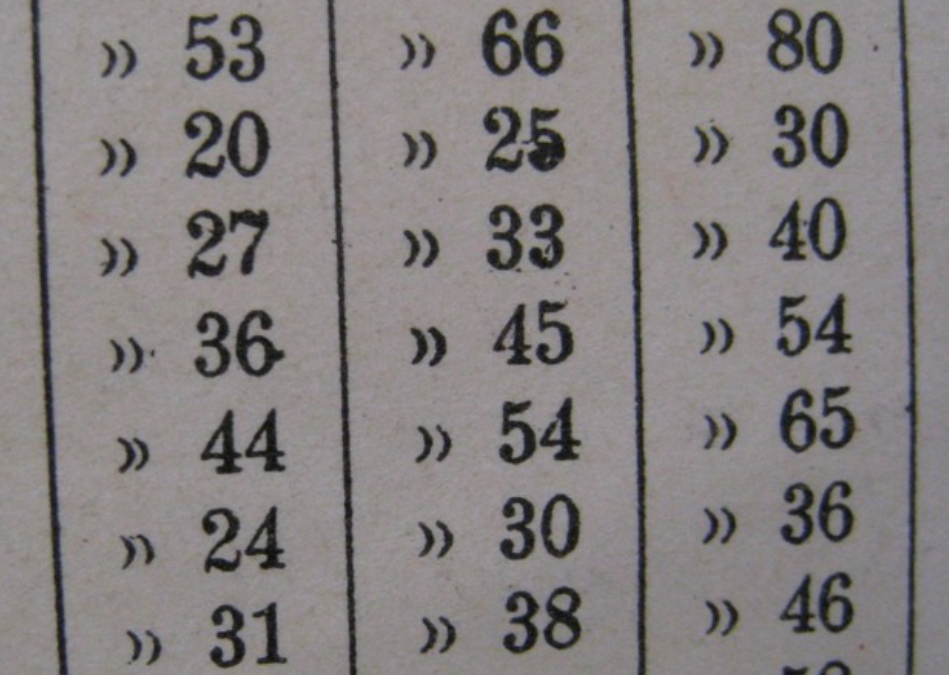
比例衬里数字的好处在于其看起来更相等,因为数字的形式和间距可以补偿不同的笔画密度。
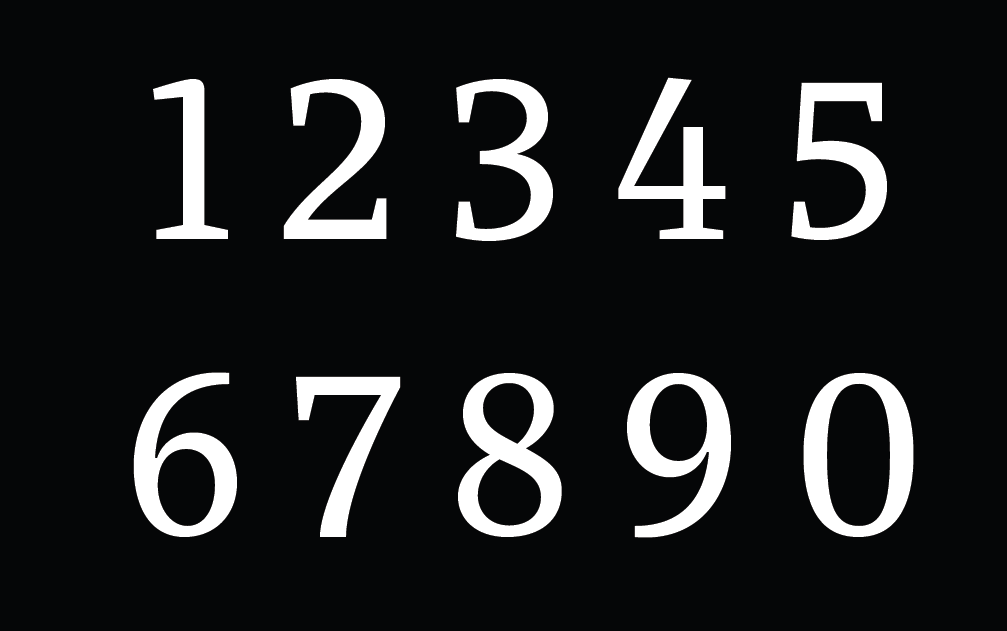
排列或者老式的数字
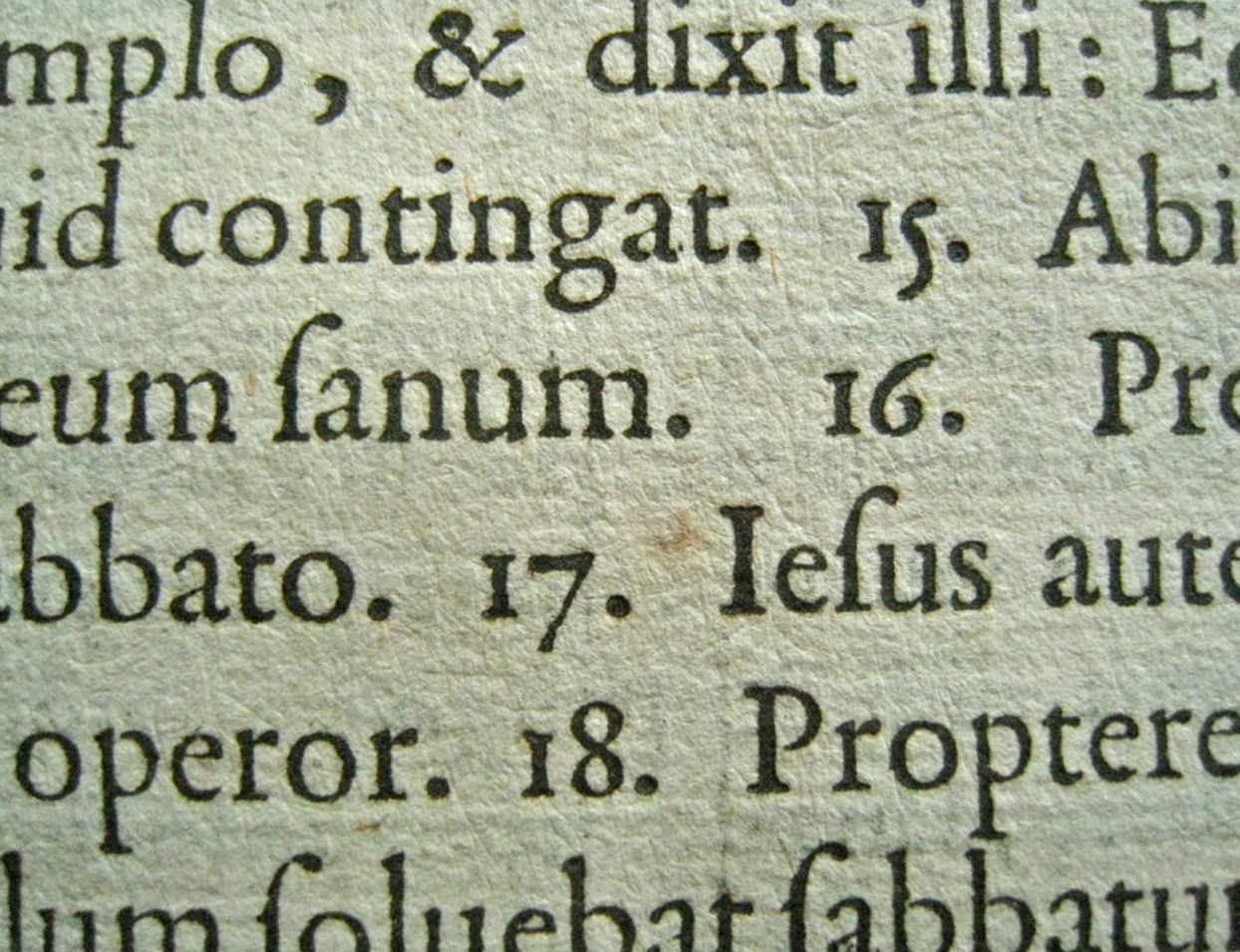
扁平数字是历史上的术语中相对较新的发明。在其存在前有许多老式的比例数字。如果你希望数字和文字混合并使用文字的样式,那么老式的数字是有帮助的。
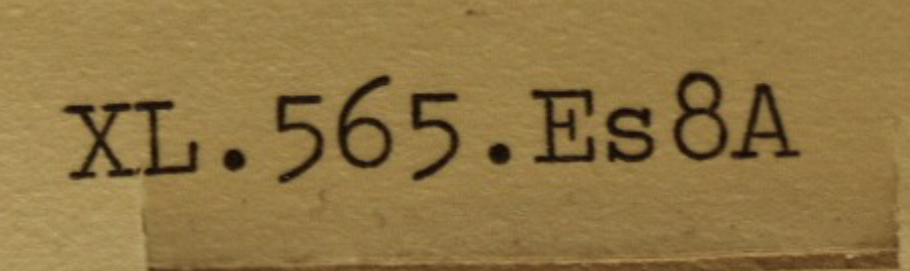
扁平老式数字是非常少见的。它在年报中有用,在年报中你想要老式数字的感觉,扁平间距是这种类型文件的典型。上面的图片来自打印机制作的图书馆分类卡。
混合类型数字
混合(hybrid)数字并不使用字体的大写高度和 x 高度,而是使用它们自己的高度。术语“混合”指的是老式与衬里样式的数字。使用混合类型数字的字体包括 Georgia 和 Google 网页字体 Merriweather 和 Donegal。Merriweather 字体的零、大写字母 O、0、1、2、3 等字形展示在下面。